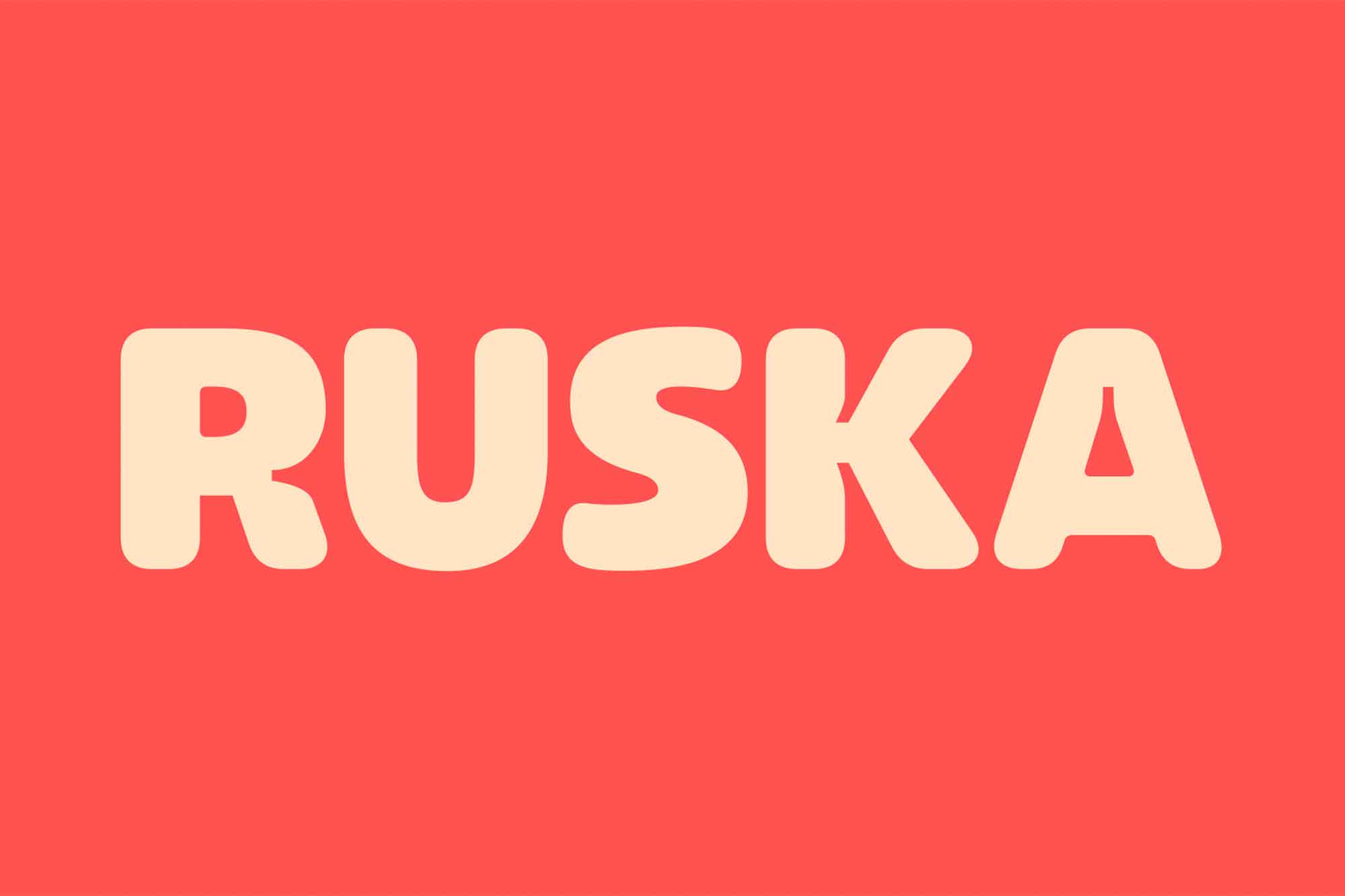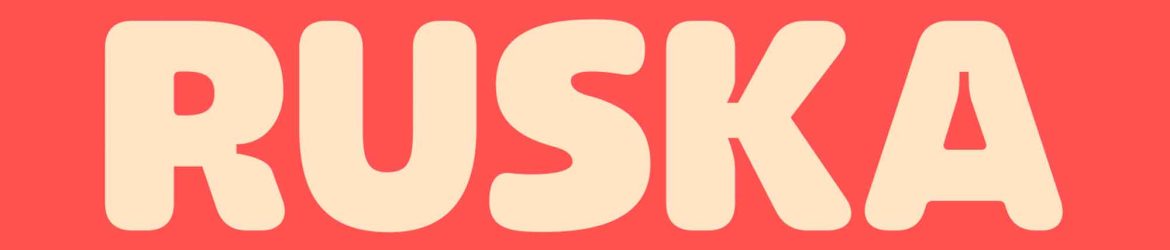
Ruska é uma fonte de display com um design amigável que destaca-se pelo seu design com canto arredondado e espirais de tinta. Este tipo de fonte é multifuncional e adequado para uma variedade de aplicações, desde materiais de marketing até layouts de jornal. Seu formato delicado e arredondado, que inclui pequenos arredondamentos e espirais de tinta, oferece um aspecto atraente e sofisticado que se destaca. Ruska é uma excelente escolha para qualquer design que precise de um toque de elegância e modernidade. Seja em uma embalagem de produto, um site ou material publicitário, Ruska Display Font irá brilhar, criando um impacto visual notável em qualquer aplicação.